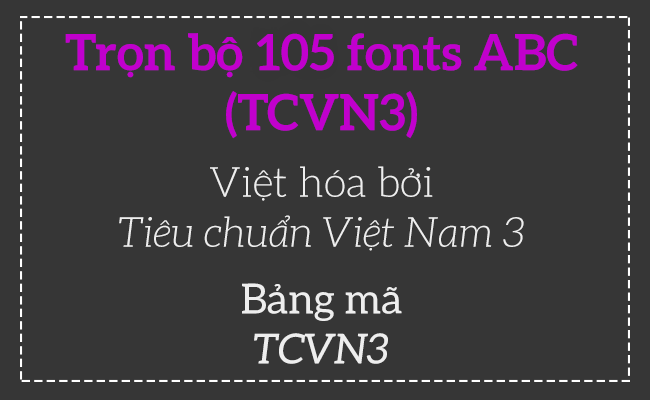
Bộ Font: TCVN3
Phân loại: Đa dạng màu sắc
Kiểu chữ: Serif
Bộ font TCVN3 là một trong những bộ mã chữ phổ biến tại Việt Nam thuộc bộ font chữ Việt hóa trước khi Unicode trở thành tiêu chuẩn quốc tế. Bộ font này cung cấp các ký tự tiếng Việt theo chuẩn TCVN3, giúp hiển thị và xử lý các tài liệu văn bản được tạo ra từ những thập kỷ trước một cách chính xác. Việc cài đặt bộ font TCVN3 miễn phí sẽ giúp bạn dễ dàng truy cập và chỉnh sửa các tài liệu cũ mà không gặp phải lỗi hiển thị ký tự, đảm bảo rằng nội dung văn bản vẫn giữ nguyên độ chính xác và toàn vẹn như ban đầu.